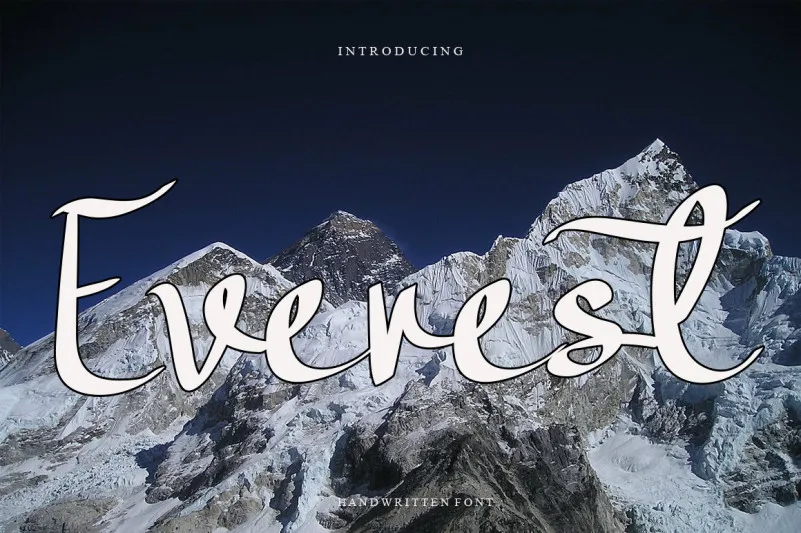
Esta é uma fonte cursiva escrita a mão com características levemente delicadas e leve. Suave e encantadora, essa fonte se destaca para design ideias variadas. Ela traz um toque alegre e romântico à cada projeto que usa. Este script será uma ótima adição para qualquer designer em busca de algo agradável e inspirador para seus projetos gráficos. A “Everest Font”, da designer LevinCreative, é perfeita para aqueles que buscam uma fonte elegante com um toque delicado e encantador. Com ela, o seu próximo design será definitivamente mais colorido e alegre. Não deixe de experimentar essa fantástica opção de fontes cursivas.